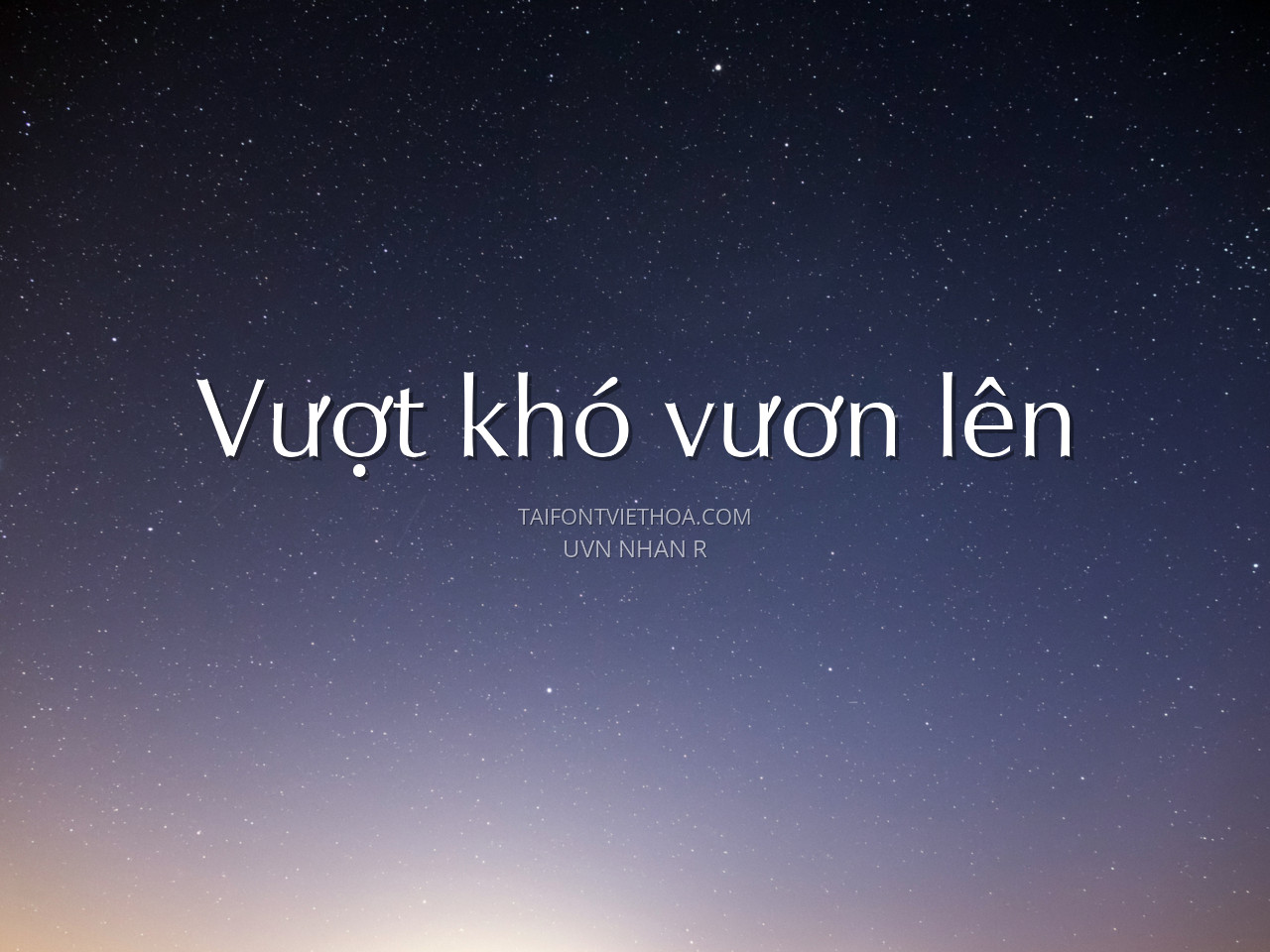
Font việt hóa UVN Nhan
Giới thiệu về font UVN Nhan
UVN Nhan là một font chữ hiện đại, tinh tế với phong cách thiết kế thanh thoát, nhẹ nhàng. Cái tên “Nhan” có thể gợi liên tưởng đến sự thanh lịch, nhã nhặn – đúng như cách font này thể hiện trong từng nét chữ. Font được sưu tầm và chia sẻ bởi thành viên Font Chuẩn, đồng thời được taifontviethoa.com tuyển chọn để phục vụ nhiều dự án thiết kế hiện đại, chuyên nghiệp và mang hơi hướng tối giản.
Đặc điểm thiết kế và ứng dụng của UVN Nhan
Font UVN Nhan mang cấu trúc sans-serif rõ ràng, gọn gàng, với các nét chữ mảnh, thoáng và đều. Kiểu chữ không chân này giúp tăng tính hiện đại và linh hoạt khi sử dụng trên đa dạng nền tảng. Thiết kế chữ có độ cao đồng đều, độ rộng chuẩn, mang lại hiệu quả thẩm mỹ cao khi trình bày văn bản dài hoặc tiêu đề thương hiệu.
Ứng dụng lý tưởng: website giới thiệu công ty, hồ sơ thương hiệu, tài liệu doanh nghiệp, giao diện người dùng, brochure công nghệ. Ngành nghề phù hợp: công nghệ, startup, truyền thông số, thiết kế web, thương hiệu sáng tạo.